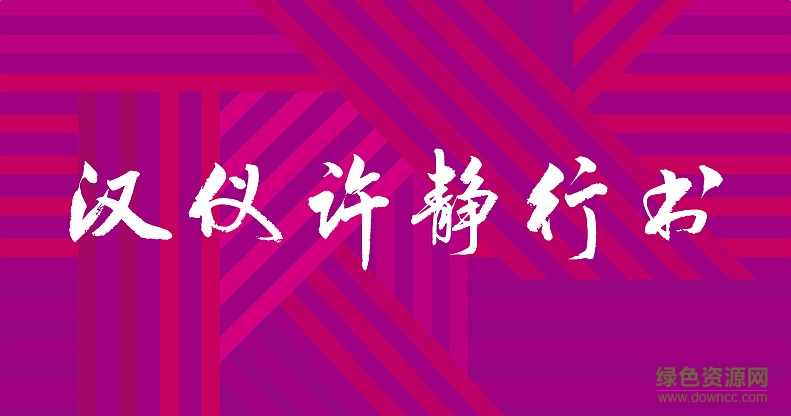
漢儀許靜行書(shū)字體是由著名書(shū)法家許靜為背景成立的一款漢儀字體,其筆畫(huà)弧度優(yōu)美,盡顯行書(shū)字體的放浪不羈,整體效果非常整齊好看,深受廣大年輕人喜愛(ài),感興趣的朋友歡迎到綠色資源網(wǎng)下載體驗(yàn)!
漢儀許靜行書(shū)字體是一款應(yīng)用于藝術(shù)設(shè)計(jì)方面的簡(jiǎn)體中文字體,該字體筆畫(huà)粗壯,尾部的甩尾有力且有豐富的筆觸細(xì)節(jié),大字效果突出且引人注目;并且最大程度還原作者書(shū)寫(xiě)字形,細(xì)節(jié)表現(xiàn)完整,且字庫(kù)完整,可以廣泛應(yīng)用于名片設(shè)計(jì)、新聞媒體、宣傳海報(bào)、ppt、影視制作以及內(nèi)容用字等領(lǐng)域。